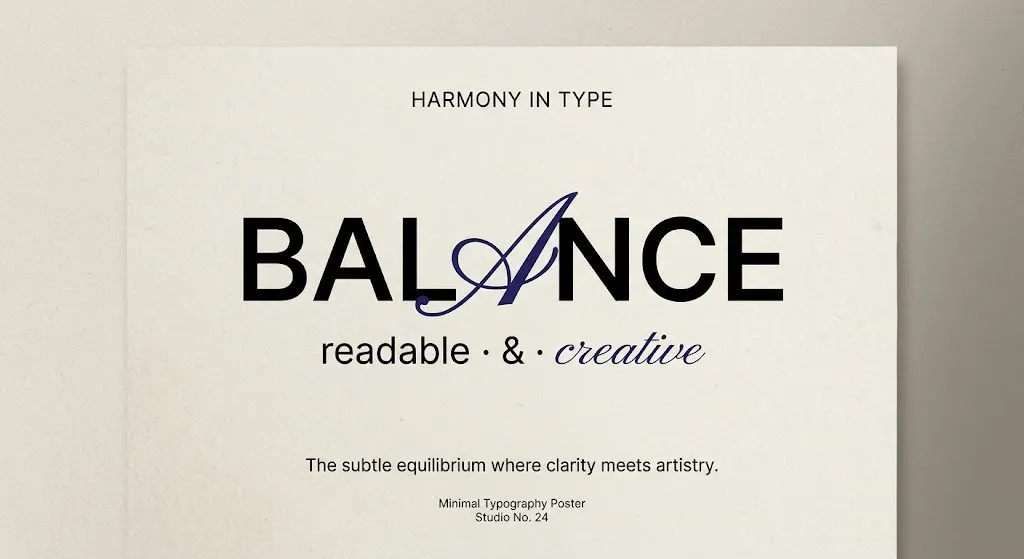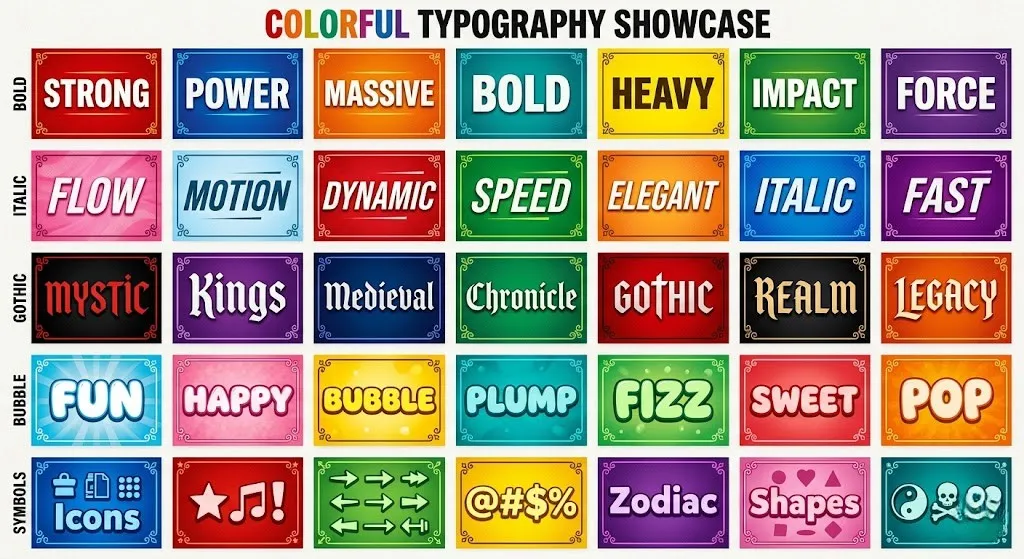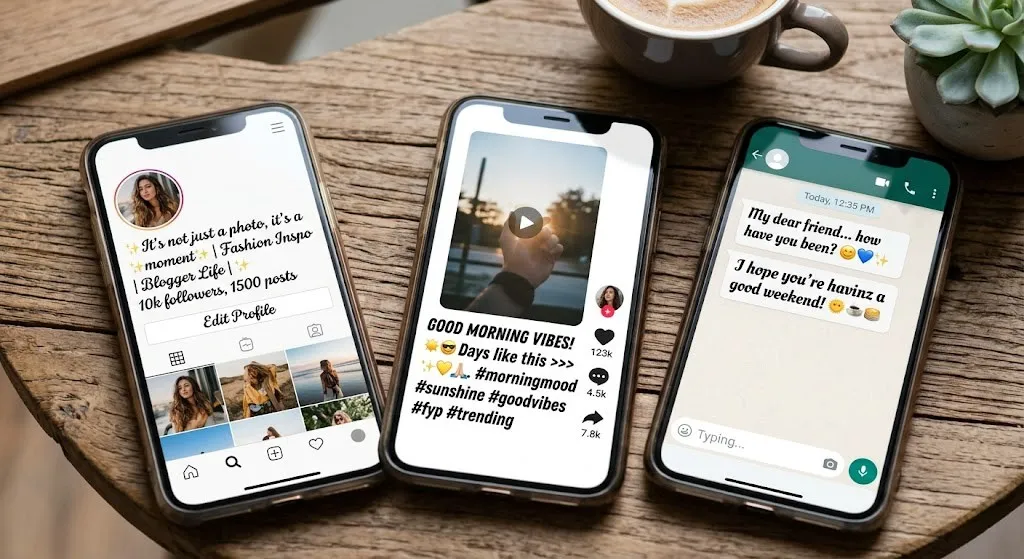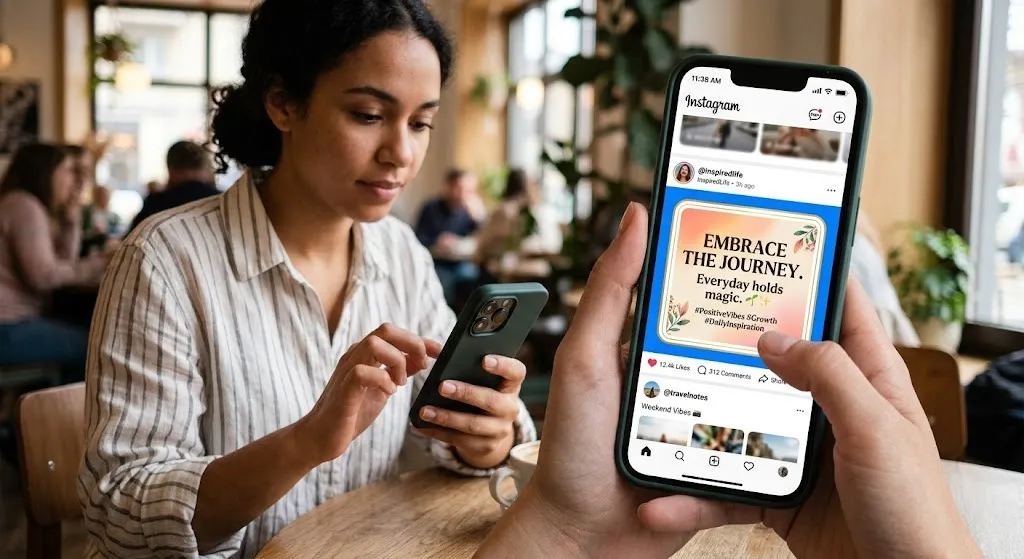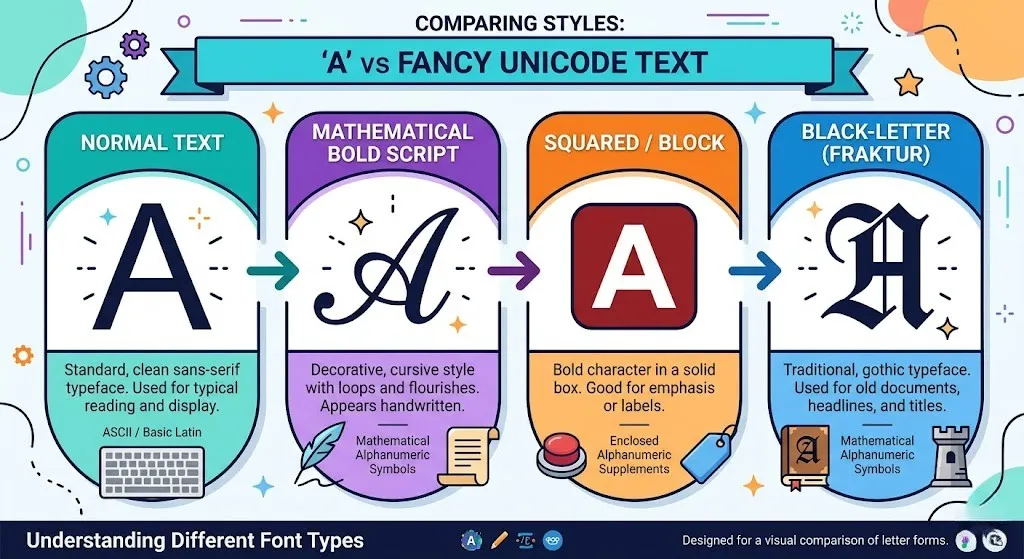
Was ist ein Schriftgenerator? Einfach erklärt & Guide
Ein Schriftgenerator ist ein Online-Tool, mit dem du normalen Text in stylische Schriftarten, Symbole oder fancy Textstile umwandeln kannst. Diese Texte kannst du anschließend kopieren und auf Plattformen wie Instagram, TikTok, Facebook oder WhatsApp verwenden.
Technisch nutzt ein Schriftgenerator keine echten Schriftarten, sondern sogenannte Unicode-Zeichen. Dabei werden normale Buchstaben durch ähnliche Symbole ersetzt (z. B. 𝓽𝓮𝔁𝓽 oder ⓣⓔⓧⓣ), die wie besondere Fonts aussehen.
Einleitung
Normaler Text wirkt auf Social Media oft langweilig und geht schnell im Feed unter. Gerade auf Plattformen wie Instagram oder TikTok zählt der erste Eindruck – und einfacher Standardtext reicht dafür meist nicht aus.
Viele Nutzer möchten ihre Texte auffälliger, kreativer und individueller gestalten, um mehr Aufmerksamkeit zu bekommen und sich von anderen abzuheben.
Genau hier kommt der Schriftgenerator ins Spiel: Er verwandelt normalen Text in stylische Schriftarten, die sofort ins Auge fallen und deine Inhalte interessanter machen.
Social Media Feed mit auffälligem stylischem Text
Was ist ein Schriftgenerator?
Ein Schriftgenerator ist ein Tool, mit dem du normalen Text in verschiedene stylische Schriftarten und Designs umwandeln kannst. Diese Texte lassen sich einfach kopieren und z. B. auf Instagram oder TikTok verwenden.
Einfache Definition
Ein Schriftgenerator wandelt deinen eingegebenen Text automatisch in verschiedene Schriftstile um – zum Beispiel fett, kursiv oder dekorativ. So kannst du deine Texte optisch aufwerten.
Unterschied zu echten Schriftarten
Im Gegensatz zu echten Fonts (die installiert werden müssen) nutzt ein Schriftgenerator Unicode-Zeichen. Das sind spezielle Symbole, die wie Buchstaben aussehen, aber technisch normale Zeichen sind.
👉 Du brauchst also keine Software oder Installation
Einsatzbereiche
Schriftgeneratoren werden vor allem genutzt für:
• Social Media Bios & Beiträge
• Nachrichten (z. B. in WhatsApp)
• Kommentare und Profile
• Kreative Texte & Designs
👉 Ziel: Mehr Aufmerksamkeit und individuelle Gestaltung
Wie funktioniert ein Schriftgenerator technisch?
Ein Schriftgenerator wandelt normalen Text in stylische Varianten um – meist ohne echte Schriftarten zu verändern. Besonders auf Plattformen wie Instagram oder TikTok kommt dabei eine einfache, aber clevere Technik zum Einsatz.
Unicode Erklärung
Die meisten Online-Schriftgeneratoren nutzen Unicode-Zeichen. Das sind spezielle Symbole aus einem weltweiten Zeichensatz, die wie normale Buchstaben aussehen (z. B. A → 𝓐, 𝔄, 🅰).
👉 Der Generator ersetzt also Buchstaben durch ähnliche Zeichen
Vergleich normale Schrift und Unicode Schriftarten
Warum keine echten Fonts genutzt werden
Echte Schriftarten (Fonts) müssten installiert werden und funktionieren nicht überall gleich.
Unicode-Zeichen dagegen:
• funktionieren plattformübergreifend
• benötigen keine Installation
• können überall eingefügt werden
👉 Deshalb nutzen Schriftgeneratoren Unicode statt echte Fonts
Copy & Paste Prinzip
Die Nutzung ist ganz einfach:
• Text eingeben
• Stil auswählen
• Ergebnis kopieren
• In Social Media einfügen
👉 Der Text bleibt technisch „normal“, sieht aber stylisch aus
Wo kann man Schriftgeneratoren nutzen?
Schriftgeneratoren lassen sich auf vielen Plattformen einsetzen, besonders im Bereich Social Media. Du kannst die generierten Texte einfach kopieren und direkt einfügen.
Social Media Plattformen
• Instagram
👉 Für Bio, Captions und Kommentare – ideal für auffällige Profile
• TikTok
👉 Für Beschreibungen, Hooks und kreative Texte
• WhatsApp
👉 Für Status, Nachrichten und Profil-Bio
• Facebook
👉 Für Beiträge, Kommentare und Profilinfos
• X (formerly Twitter)
👉 Für Tweets, Threads und Profiltexte
Schriftgenerator Nutzung auf Social Media Plattformen
Wer kann einen Schriftgenerator nutzen?
Ein Schriftgenerator ist für jeden geeignet, der Texte kreativer und auffälliger gestalten möchte. Die Nutzung ist einfach und funktioniert meist per Copy & Paste.
Content Creator
Creator auf Plattformen wie Instagram oder TikTok nutzen Schriftgeneratoren, um ihre Inhalte visuell hervorzuheben und mehr Aufmerksamkeit zu bekommen.
Social Media Manager
Für Marketing und Branding sind stylische Texte ein Vorteil. Social Media Manager nutzen sie, um Posts, Bios und Kampagnen ansprechender zu gestalten.
Gamer
Gamer verwenden stylische Schriftarten für Nicknames, Profile oder Chats, um sich von anderen Spielern abzuheben.
Normale Nutzer
Auch im Alltag sind Schriftgeneratoren beliebt – z. B. für WhatsApp Nachrichten, Status oder persönliche Texte.
Vorteile eines Schriftgenerators
Ein Schriftgenerator ist ein einfaches, aber sehr effektives Tool, um Texte schnell kreativer zu gestalten – besonders auf Plattformen wie Instagram oder TikTok.
Mehr Aufmerksamkeit
Stylische Schriftarten heben deinen Text vom Standard ab. Dadurch fällt dein Inhalt im Feed schneller auf.
Bessere Engagement-Rate
Auffällige Texte sorgen dafür, dass Nutzer eher reagieren – z. B. mit Likes, Kommentaren oder Shares.
Einfache Nutzung
Die Bedienung ist sehr simpel:
• Text eingeben
• Stil auswählen
• Kopieren
👉 Keine Designkenntnisse erforderlich
Keine Installation nötig
Die meisten Schriftgeneratoren funktionieren direkt im Browser. Du brauchst keine App oder Software zu installieren.
Nachteile & Einschränkungen
Auch wenn Schriftgeneratoren viele Vorteile bieten, gibt es einige Punkte, die du beachten solltest:
Nicht überall kompatibel
Nicht alle Unicode-Schriftarten funktionieren auf jeder Plattform oder jedem Gerät gleich. In manchen Apps werden bestimmte Zeichen gar nicht oder falsch angezeigt.
Lesbarkeit kann leiden
Zu ausgefallene oder dekorative Schriftarten sind oft schwer zu lesen. Das kann dazu führen, dass Nutzer deinen Text schnell überspringen.
Barrierefreiheit (Screenreader Problem)
Viele stylische Schriftarten bestehen aus speziellen Unicode-Zeichen. Screenreader können diese oft nicht richtig vorlesen, was die Zugänglichkeit für sehbehinderte Nutzer einschränkt.
Beispiele für Schriftgenerator-Stile
Ein Schriftgenerator bietet viele verschiedene Textstile, die deinen Inhalt auf Plattformen wie Instagram oder Facebook auffälliger machen.
Fett
• 𝐁𝐨𝐥𝐝 𝐓𝐞𝐱𝐭
• 𝗙𝗮𝘁 𝗦𝘁𝘆𝗹𝗲
👉 Ideal, um wichtige Wörter hervorzuheben
Kursiv
• 𝘐𝘵𝘢𝘭𝘪𝘤 𝘛𝘦𝘹𝘵
• 𝒮𝓉𝓎𝓁𝒾𝓈𝒽 𝒮𝓉𝓎𝓁𝑒
👉 Elegant und professionell
Kreativ
• 𝔊𝔬𝔱𝔥𝔦𝔠 𝔖𝔱𝔶𝔩𝔢
• Ⓑⓤⓑⓑⓛⓔ Ⓣⓔⓧⓣ
• 𝚂𝚝𝚢𝚕𝚒𝚜𝚑 𝙼𝚘𝚗𝚘
👉 Für einzigartige und auffällige Designs
Symbole
• ★ Text ★
• ✨ Fancy Text ✨
• ⚡ Name ⚡
👉 Perfekt, um Text zusätzlich hervorzuheben
Beispiele für verschiedene Schriftgenerator Stile
Häufige Fehler vermeiden
Auch beim Einsatz von Schriftgeneratoren solltest du typische Fehler vermeiden, damit dein Text auf Plattformen wie Instagram oder TikTok gut wirkt.
Zu viele Styles
Wenn du zu viele verschiedene Schriftarten kombinierst, wirkt dein Text unruhig und chaotisch. Bleibe bei 1–2 Stilen für ein klares Design.
Unlesbarer Text
Zu ausgefallene oder verschnörkelte Schriftarten sind oft schwer zu lesen. Wenn Nutzer deinen Text nicht sofort verstehen, verlierst du Aufmerksamkeit.
Falsche Nutzung
Stylische Schriftarten sollten gezielt eingesetzt werden – z. B. für Highlights oder wichtige Wörter. Wenn der ganze Text „fancy“ ist, verliert er seine Wirkung.
Tipps für die richtige Nutzung
Damit dein Text mit einem Schriftgenerator wirklich wirkt, solltest du ihn bewusst einsetzen – besonders auf Plattformen wie Instagram oder TikTok.
Weniger ist mehr
Nutze nur wenige Schriftstile. Zu viele verschiedene Designs wirken schnell unruhig und verlieren ihre Wirkung.
Fokus auf Lesbarkeit
Dein Text sollte immer leicht zu lesen sein. Vermeide zu komplizierte oder verschnörkelte Schriftarten.
Strategisch einsetzen
Setze stylische Schriftarten gezielt ein – z. B. für wichtige Wörter, Überschriften oder Highlights.
Balance zwischen Lesbarkeit und kreativen Schriftarten
Fazit
Ein Schriftgenerator ist ein einfaches und effektives Tool, um Texte schnell kreativer und auffälliger zu gestalten. Durch die Nutzung von Unicode-Zeichen kannst du deine Inhalte ohne Installation individuell anpassen und auf Plattformen wie Instagram oder TikTok hervorheben.
Für die beste Wirkung solltest du stylische Schriftarten gezielt einsetzen: Halte deine Texte lesbar, nutze nur wenige Styles und setze Highlights bewusst ein.
👉 Empfehlung: Verwende Schriftgeneratoren strategisch, um Aufmerksamkeit zu steigern und deine Inhalte professioneller wirken zu lassen.